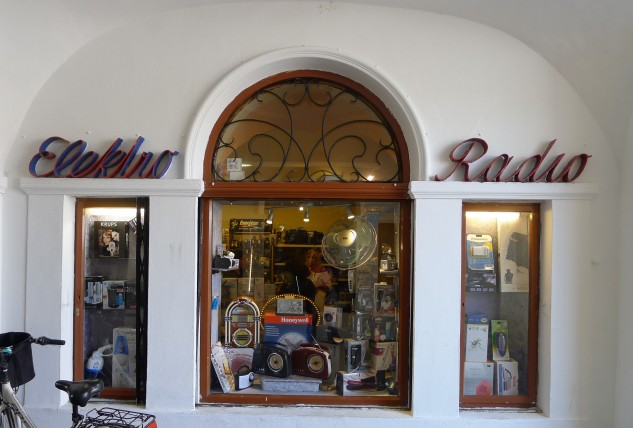
Elektro Radio
Eines der wunderbaren, langsam aussterbenden Geschäfte, die wir schon seit unserer Kindheit kennen. Die ordentliche Schreibschrift birgt so gar keine Elektro- oder Technikaffinität, was das Ganze umso reizvoller macht. Durch die beidseitig unterschiedliche Lackierung des Flachstahls in rot und blau entsteht ein ganz wunderbaren Effekt beim Vorbeigehen.
Innsbruck, Franziskanerplatz/Altstadt